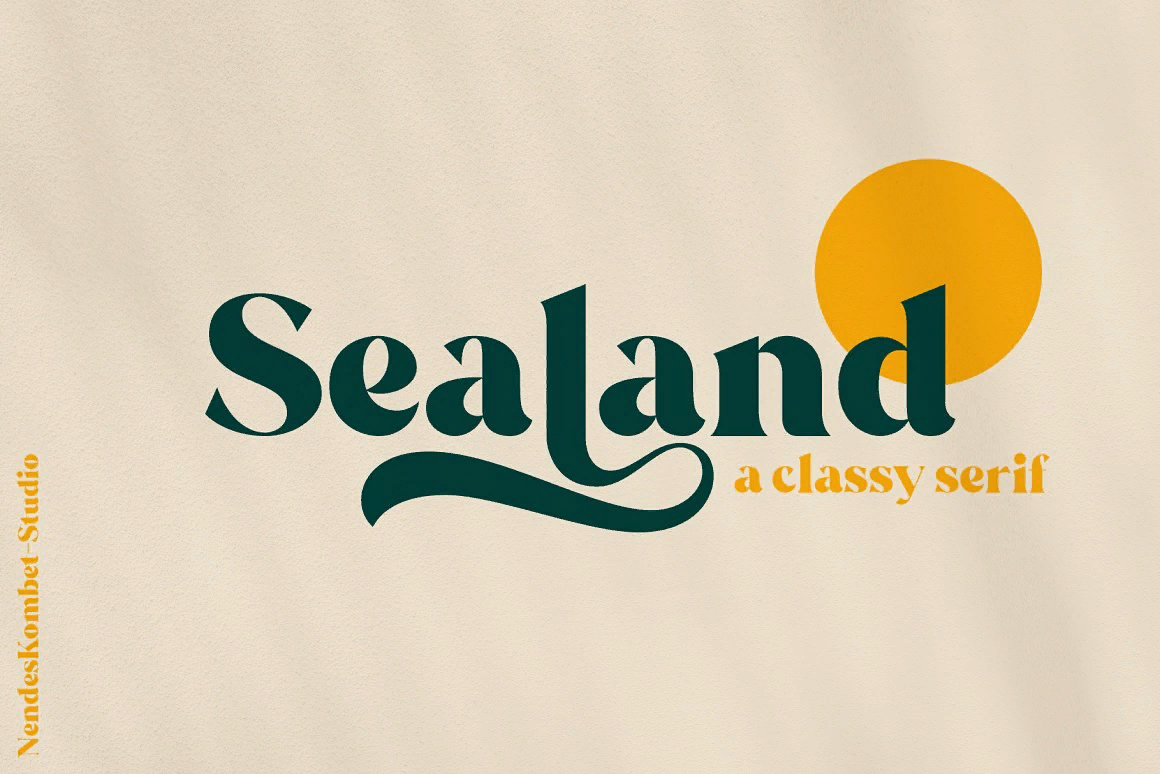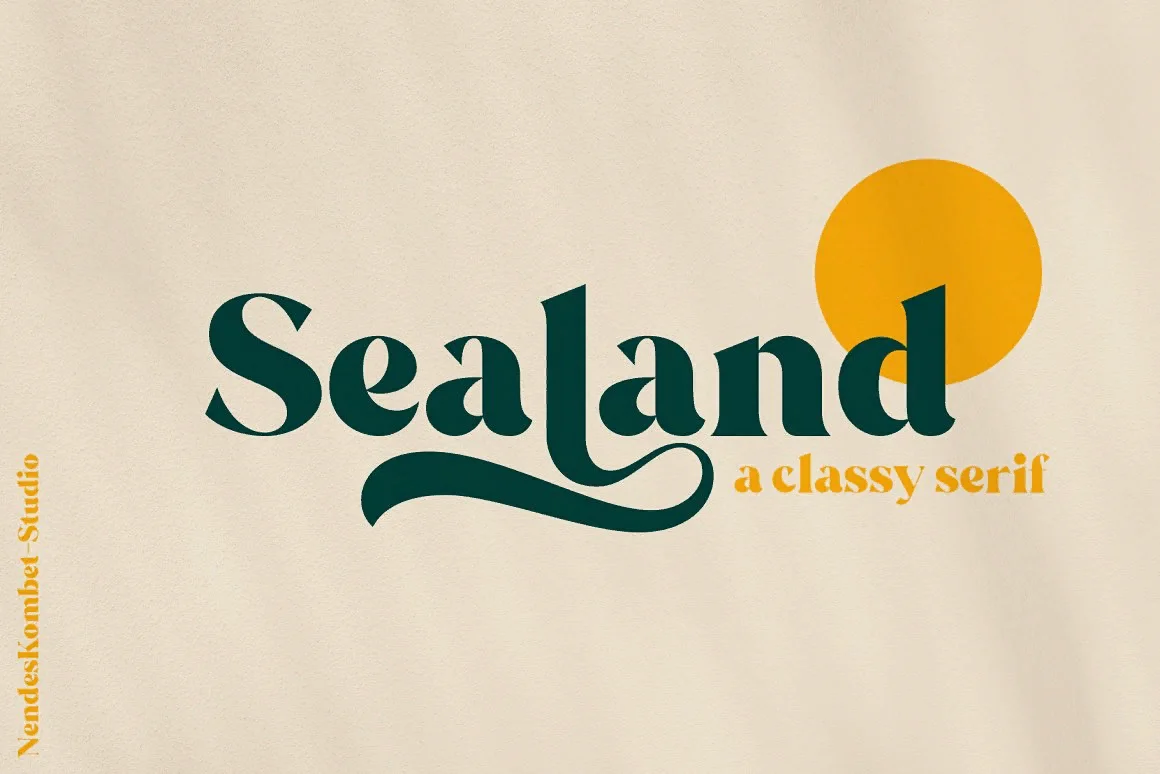
Название: Sealand Font (2021)
Sealand - это смелый и стильный шрифт с засечками.
Этот шрифт читается как сильный, уверенный и динамичный и может добавить тонны ностальгического характера в ваши проекты.